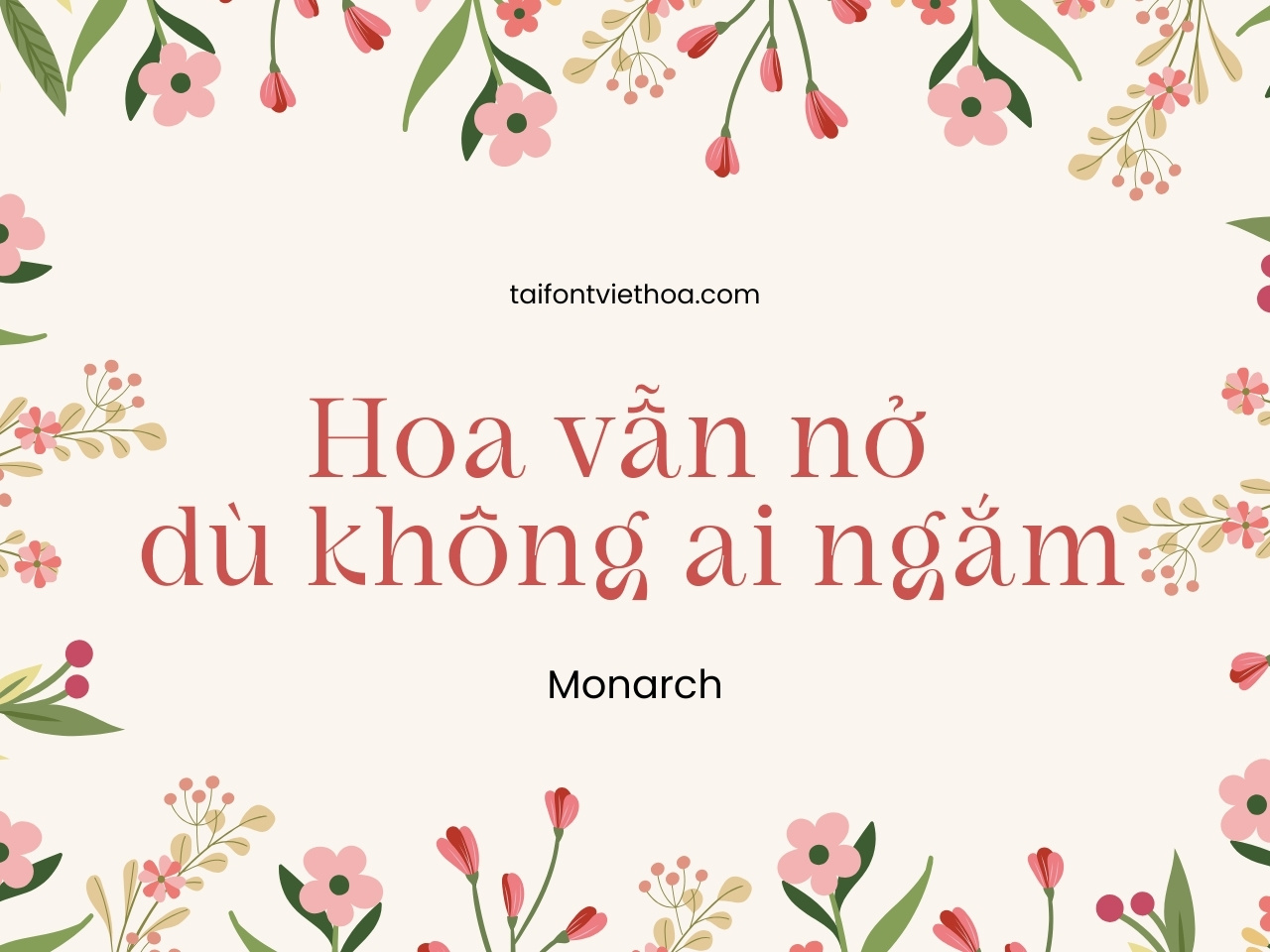
Giới thiệu về font Monarch và phiên bản Việt hóa
Monarch là một bộ font serif trang trí sang trọng, được phát triển bởi nhà thiết kế Gabriel Lam. Font gây ấn tượng với phong cách hoàng gia cổ điển, kết hợp hài hòa giữa các đường nét thanh mảnh và chi tiết trang trí uốn lượn. Được phát hành trên các nền tảng thiết kế vào năm 2022, Monarch nhanh chóng được ưa chuộng trong các dự án cao cấp nhờ vào khí chất quý phái và độ chỉn chu trong từng ký tự.
Phiên bản Việt hóa được chính Gabriel Lam thực hiện, hỗ trợ đầy đủ bảng mã Unicode, bao gồm tiếng Việt và hơn 75 ngôn ngữ quốc tế. Các dấu tiếng Việt được tinh chỉnh phù hợp với phong cách serif thanh lịch, giúp giữ vững vẻ đẹp nguyên bản của font gốc. Font Monarch được taifontviethoa.com chọn lọc, kiểm duyệt kỹ lưỡng và chia sẻ để phục vụ cộng đồng thiết kế Việt, đặc biệt những ai đang tìm kiếm một kiểu chữ cổ điển nhưng vẫn đầy tính hiện đại, dễ áp dụng thực tế.
Đặc trưng thiết kế thanh lịch và ứng dụng đa dạng
Font Monarch nổi bật với các nét chữ thanh mảnh, chiều cao chữ cái rõ ràng và điểm nhấn ở các nét cong đầy nghệ thuật. Cấu trúc serif truyền thống kết hợp cùng chi tiết bo tròn mềm mại mang lại cảm giác cao cấp, lãng mạn và sang trọng. Font có hệ thống ký tự trang trí độc đáo, phù hợp với cả tiêu đề lớn và các dòng trích dẫn ngắn.
Monarch là sự lựa chọn lý tưởng cho các lĩnh vực như thiệp cưới, mỹ phẩm, thời trang cao cấp, bất động sản, giáo dục và các thương hiệu mang tính nghệ thuật. Font cũng được sử dụng nhiều trong các thiết kế cho lễ hội, sự kiện tình yêu như Valentine hoặc Giáng sinh – nơi cần thể hiện cảm xúc và sự tinh tế thị giác.